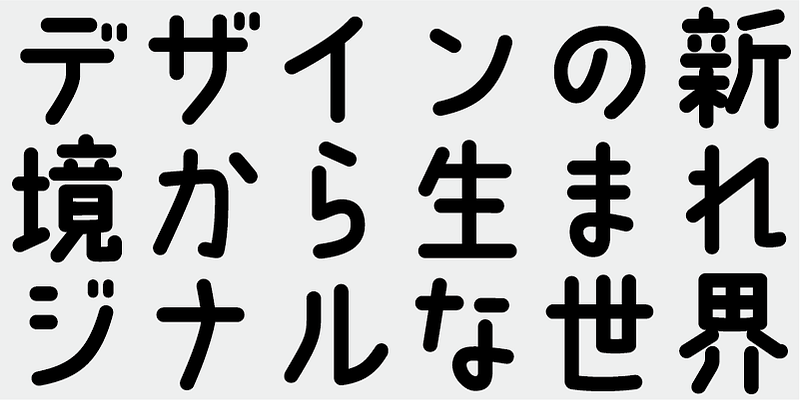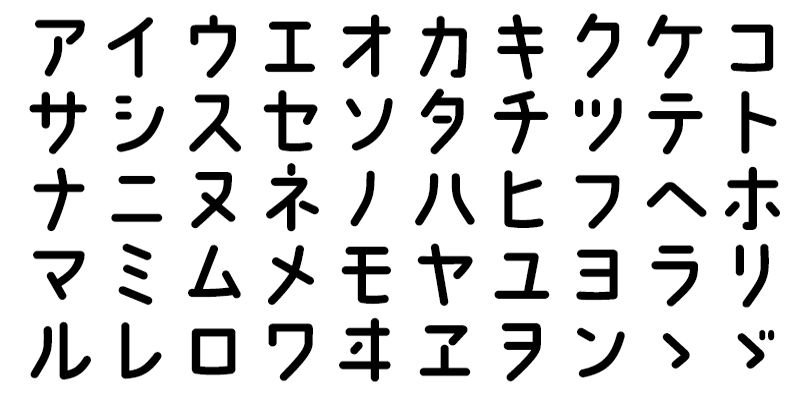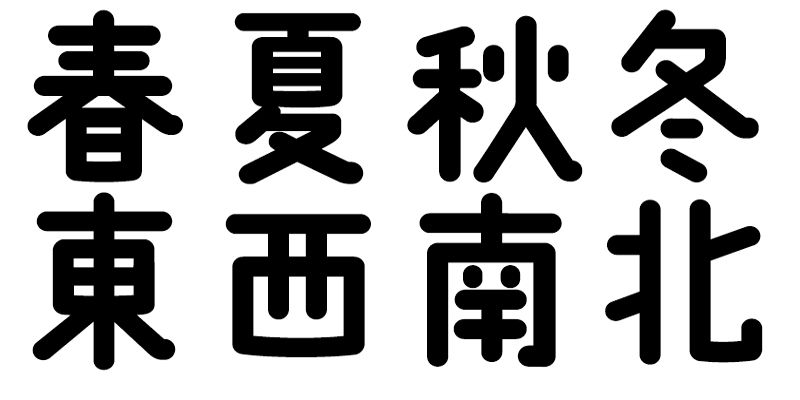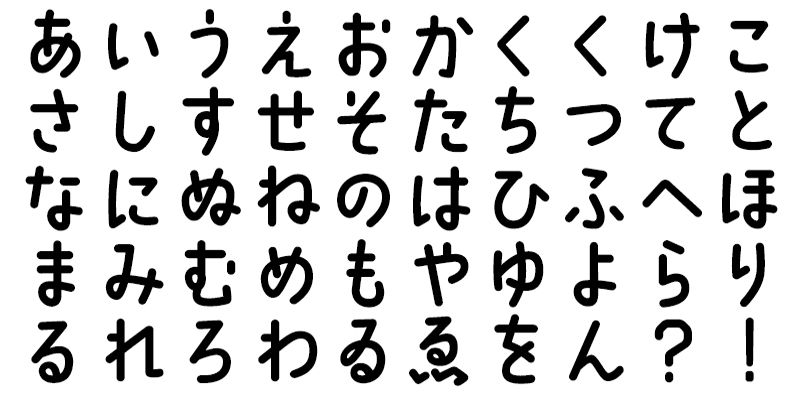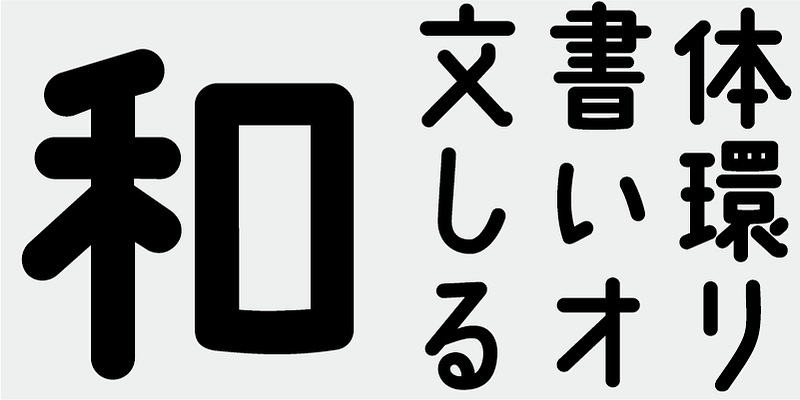
この書体は、文字で表現された言葉を通じて意味を伝えることへの感動、感謝、思い出を伝えたいという思いでデザインされました。
このフォントには、新聞社、出版社、国語研究所等の使用頻度表から選んだ上位 1,000 個の漢字に加え、206 個の両仮名および約物が含まれています。
FONT1000はそれぞれが独立したフォントデザイナーの集合体です。フォント制作はJISの約7,000字が基準です。しかし、全てのフォントに7,000字が必要なのか。写植の時代でもそれよりもはるかに少ない文字数でした。そんな素朴な疑問から、FONT1000は日本文を組むのに必要最小限な漢字として、新聞社、出版社、国語研究所等の使用頻度表から選んだ、ベスト1,000の漢字に両仮名および約物を加え、2001年の結成以来、フォント制作にチャレンジしてきました。当初は、25名、25書体の参加でしたが、その後、より多くの文字を含むフォントの開発も行うようになり、書体数も130、デザイナーも40名近くにまでなっています。